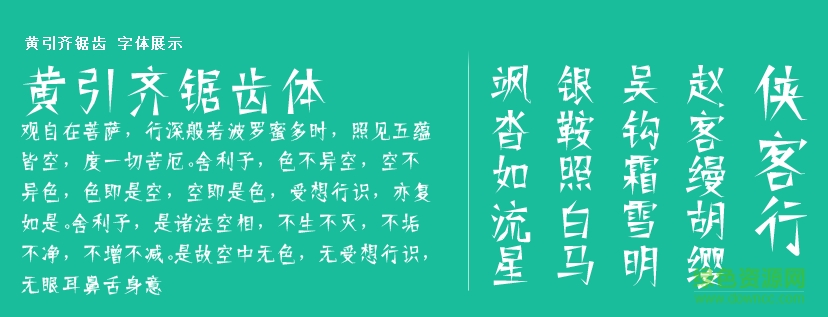
黃引齊鋸齒字體是一款有著不規(guī)整筆畫造型的黃引齊字體,如果鋸齒形而得名,讓字體筆畫通過三角形拼接起來,好看又有趣,喜歡的朋友快來綠色資源網(wǎng)下載吧!
黃引齊鋸齒字體是黃引齊字庫推出的藝術字體,文字筆畫均采用鋸齒形,打破傳統(tǒng)一筆一劃的規(guī)整和傳統(tǒng),給人眼前一亮,同時加黑加粗的字體讓人印象深刻。